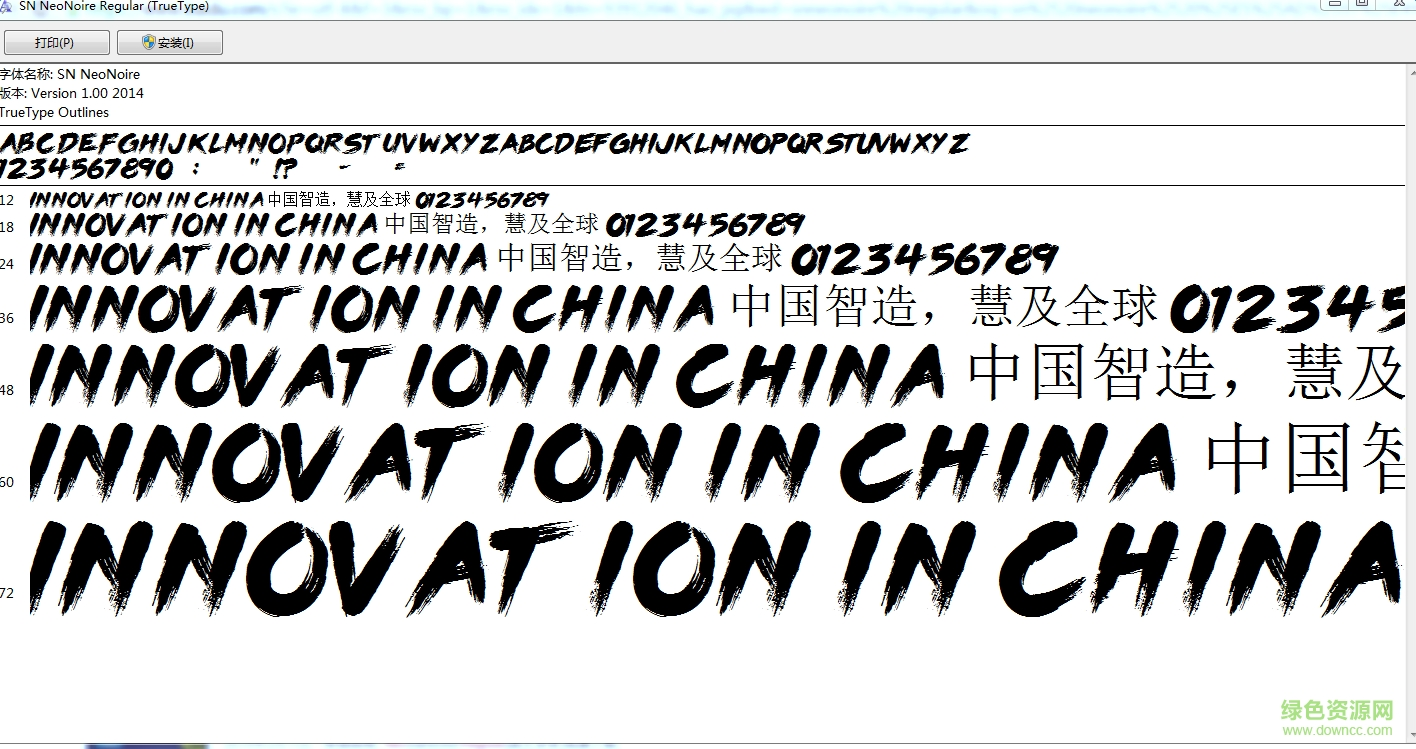
snneonoire regular字體
snneonoire regular字體是一款斜體的英文字體,線條流暢靈動(dòng),細(xì)節(jié)出色,個(gè)性鮮明,常常應(yīng)用于藝術(shù)設(shè)計(jì)方面,感興趣的朋友歡迎在綠色資源網(wǎng)下載!
snneonoire字體介紹
snneonoirt是一款英文字體,字體效果比較潦草,喜歡英文體字的朋友可以下載使用看看效果如何。